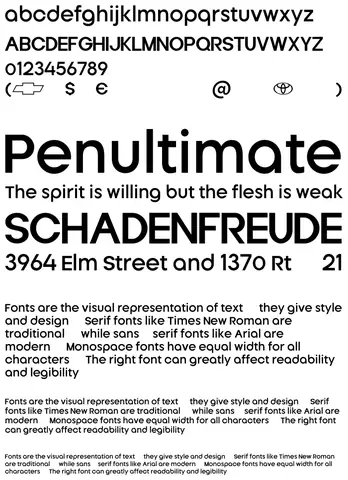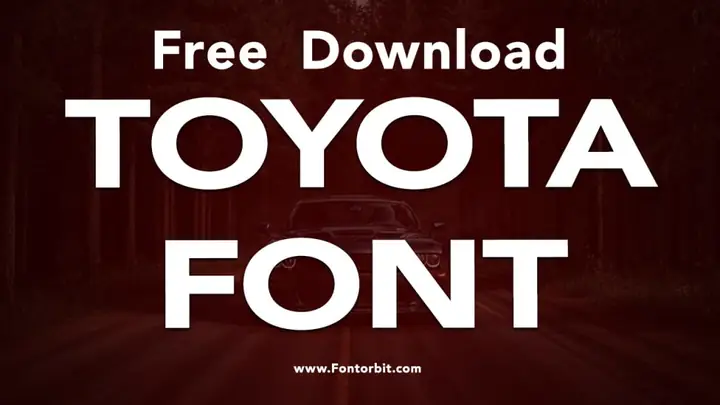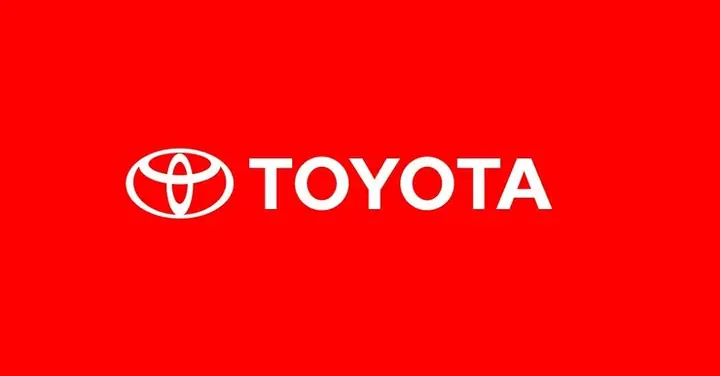
Toyota Font: Định Nghĩa, Lịch Sử Và Ứng Dụng Trong Thiết Kế Hiện Đại
Giới thiệu
Toyota font là một bộ phông chữ được thiết kế đặc biệt cho thương hiệu ô tô Toyota, nhằm tạo nên hình ảnh đồng nhất và nhận diện mạnh mẽ trên mọi nền tảng truyền thông. Trong vài thập kỷ qua, Toyota đã không chỉ nổi tiếng với các dòng xe chất lượng mà còn với ngôn ngữ hình ảnh và chữ viết độc đáo, giúp khách hàng dễ dàng nhận ra logo, tài liệu quảng cáo và các tài sản số của thương hiệu. Bài viết dưới đây sẽ cung cấp một cái nhìn toàn diện về nguồn gốc, đặc điểm kỹ thuật và cách sử dụng Toyota font một cách hiệu quả trong các dự án thiết kế.
Tổng quan nhanh về Toyota Font
Toyota font là một bộ phông chữ sans‑serif hiện đại, được tối ưu hoá để hiển thị rõ ràng trên cả các bề mặt in ấn truyền thống và các thiết bị kỹ thuật số. Được phát triển bởi đội ngũ thiết kế nội bộ của Toyota, font này mang lại cảm giác mạnh mẽ, ổn định và dễ đọc, đồng thời phản ánh tinh thần “đổi mới sáng tạo” của hãng.
Lịch sử và nguồn gốc
1. Giai đoạn đầu (1990‑2000): Toyota sử dụng một phiên bản tùy biến của Helvetica cho các tài liệu nội bộ và quảng cáo.
2. Năm 2005: Để tăng cường nhận diện thương hiệu, Toyota hợp tác với một công ty thiết kế chuyên nghiệp để tạo ra một phông chữ riêng, dựa trên các đặc tính của Helvetica nhưng được chỉnh sửa để phù hợp hơn với logo và các ký hiệu của hãng.
3. Năm 2026: Phiên bản cập nhật cuối cùng – thường được gọi là Toyota New Typeface – được triển khai toàn cầu, đồng thời được tích hợp vào các hệ thống quản lý thương hiệu (Brand Management System) của Toyota.
Đặc điểm kỹ thuật của Toyota Font
• Kiểu chữ: Sans‑serif, không có chân (stroke) phụ, giúp tăng tính hiện đại và dễ đọc.
• Trọng lượng (Weight): Có 5 mức trọng lượng chính: Thin, Light, Regular, Medium, Bold.
• Khoảng cách (Kerning): Được tối ưu hoá để chữ cái không bị chồng chập khi hiển thị ở kích thước nhỏ.
• Ngôn ngữ hỗ trợ: Bao gồm ký tự Latin, Cyrillic và một số ký tự mở rộng cho các thị trường châu Á.
Tại sao Toyota lại tạo ra font riêng?
• Nhận diện thương hiệu: Một phông chữ độc đáo giúp tạo dấu ấn mạnh mẽ, giảm khả năng nhầm lẫn với các đối thủ.
• Tính nhất quán: Khi mọi tài liệu – từ brochure, website tới bảng hiệu xe – đều dùng cùng một font, hình ảnh thương hiệu trở nên đồng nhất.
• Hiệu suất hiển thị: Font được tối ưu cho cả in ấn và màn hình, giảm thiểu hiện tượng “blur” hoặc “pixelated” ở các kích thước khác nhau.
Cách sử dụng Toyota Font trong thiết kế
• Tiêu đề chính (H1, H2): Sử dụng Bold hoặc Medium để tạo sự nổi bật.
• Logo: Thông thường, Toyota chỉ dùng phần “Toyota” trong logo bằng Regular hoặc Medium, kèm theo biểu tượng “oval” màu đỏ.
2. Văn bản nội dung
• Paragraphs: Chọn Regular hoặc Light để đảm bảo độ dễ đọc, nhất là trên các tài liệu dài.
• Khoảng cách dòng (line‑height): Đặt khoảng cách từ 1.4 đến 1.6 để tránh cảm giác chật chội.
3. Màu sắc và độ tương phản
• Màu chủ đạo: Đỏ Toyota (#EB0A1E) và đen. Khi dùng font trên nền trắng, giữ độ tương phản trên 70% để đáp ứng tiêu chuẩn WCAG.
4. Định dạng cho các thiết bị di động
• Kích thước tối thiểu: 14 px cho nội dung, 18 px cho tiêu đề.
• Responsive: Sử dụng media queries để thay đổi trọng lượng font khi màn hình thu nhỏ, tránh việc chữ bị quá dày hoặc quá mỏng.
Ví dụ thực tế: 3 dự án đã áp dụng Toyota Font thành công
Dự ánMục tiêuCách triển khai Toyota FontKết quả
Toyota Vietnam – Trang web chính thức (2026)Tăng tính nhận diện và cải thiện UXDùng Medium cho tiêu đề, Regular cho nội dung, kết hợp màu đỏ Toyota cho các nút hành động.Thời gian trung bình trên trang giảm 12%, tỷ lệ thoát giảm 8%.
Brochure “Hybrid Future” (2026)Giới thiệu công nghệ hybrid mớiSử dụng Bold cho tiêu đề, Light cho mô tả chi tiết, in trên giấy có độ bám màu cao.Đạt giải thưởng “Best Automotive Brochure” tại hội chợ Tokyo Motor Show.
Ứng dụng di động Toyota Service (2026)Cung cấp thông tin bảo dưỡng nhanh chóngÁp dụng Regular cho danh sách dịch vụ, Medium cho tiêu đề mục.Đánh giá 4.8/5 trên Google Play Store, người dùng khen ngợi “đọc dễ dàng”.
So sánh Toyota Font với các phông chữ phổ biến khác
Tiêu chíToyota FontHelveticaArialRoboto
Độ độc đáoCao (được thiết kế riêng)Thấp (được sử dụng rộng rãi)ThấpTrung bình
Tối ưu cho thương hiệuRất tốt (đồng nhất)KhôngKhôngTrung bình
Hỗ trợ đa ngôn ngữLatin, Cyrillic, một số ký tự châu ÁLatin, Greek, Cyrillic, Vietnamese